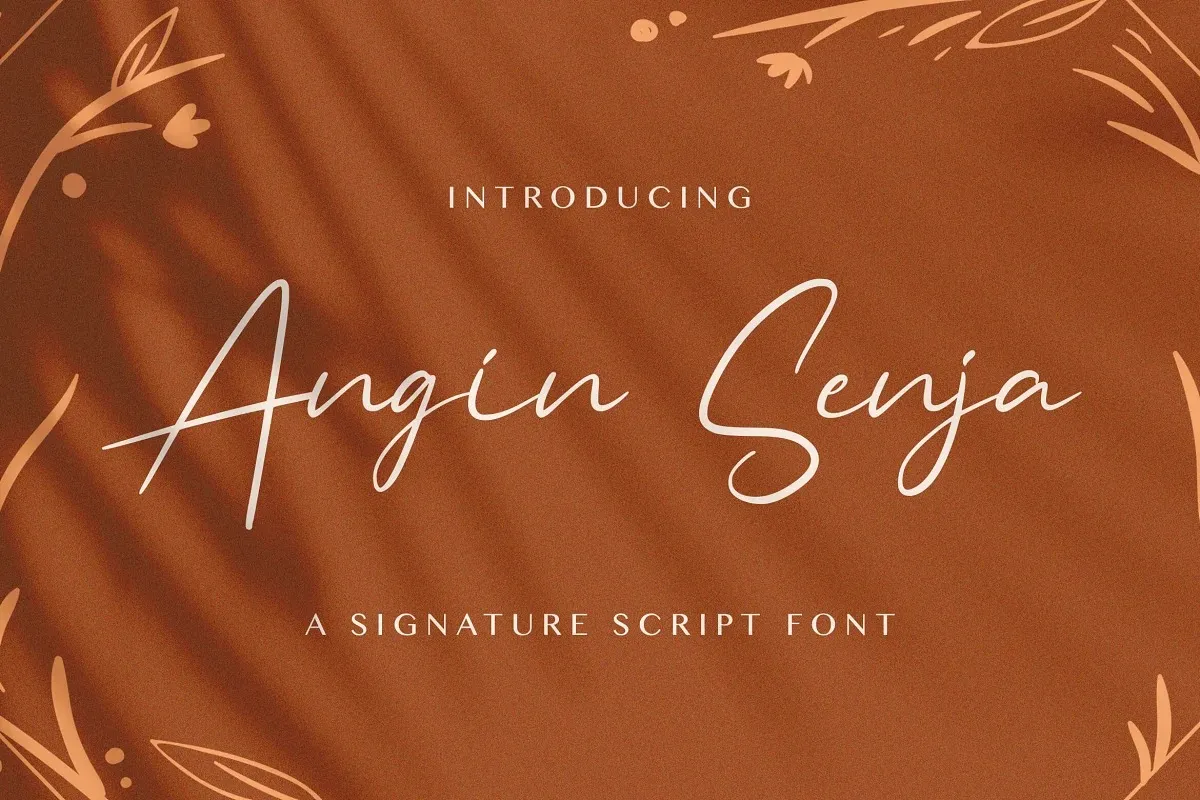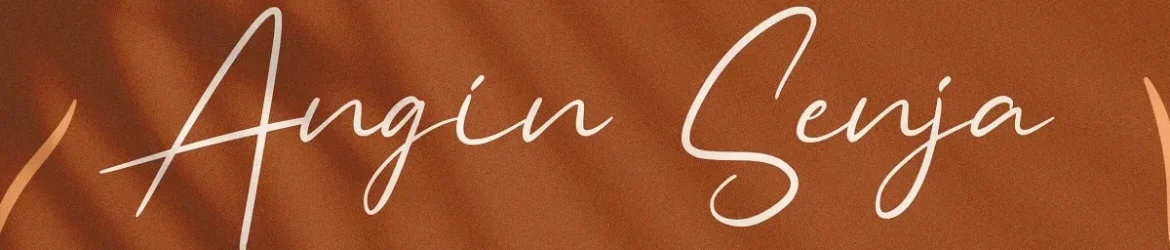
Angin Senja Font – Download Grátis
A ‘Angin Senja Font’ é uma tipografia feita à mão, perfeita para designers que buscam dar vida às suas ideias criativas. Ela retrata a elegância das letras escritas a latitudem, cada caractere sendo inspirado em um traço de pena, resultando em uma paleta vibrante e equilibrada. Esta fonte oferece os elementos necessários para moldar designs originais e inovadores, tornando-as mais únicas e personalizadas. Com a ‘Angin Senja Font’, você pode mergulhar na essência da autenticidade que se perde em muitas tipografias digitais contemporâneas. Essa fonte traz ao seu projeto uma sensação de profundidade e verdade, permitindo-lhe expressar sua visão única com estilo e sofisticação. Em um mundo cada vez mais vibrante, a ‘Angin Senja Font’ é o segredo para criar designs que realmente chamam atenção, tornando-se parte indissociável de seus trabalhos.